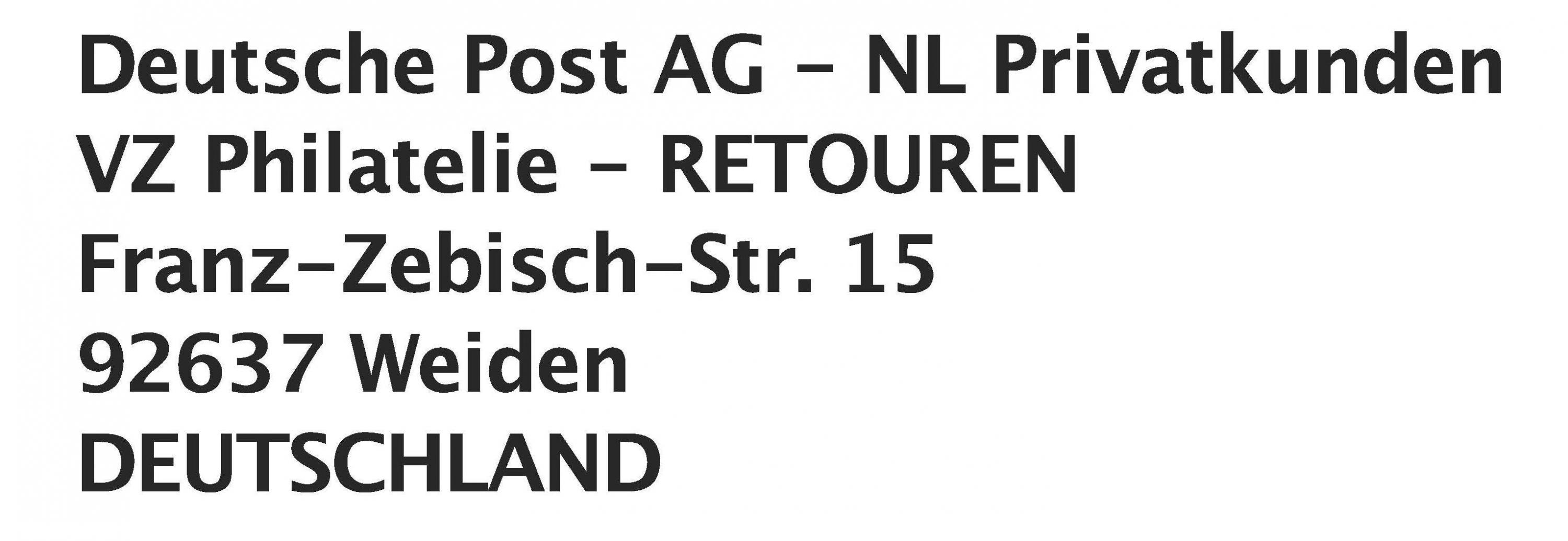
DHL-Paketschein - welche Schrift ist das?
Wie, bitte schön, soll man bei 10 Pixel Versalhöhe eine Schrift erkennen? Das grenzt an Hexerei.
Ich hab das mal vergrößert:
Da hat das Hinting so sehr an der Schrift heumgezupft, um die in der größe und Auflösung lesbar zu halten, dass vom Charakter der Schrift nicht viel übrig ist
Sorry, ich hatte es nicht besser hingekriegt. Habe nun einen besseren Ausschnitt gefunden: